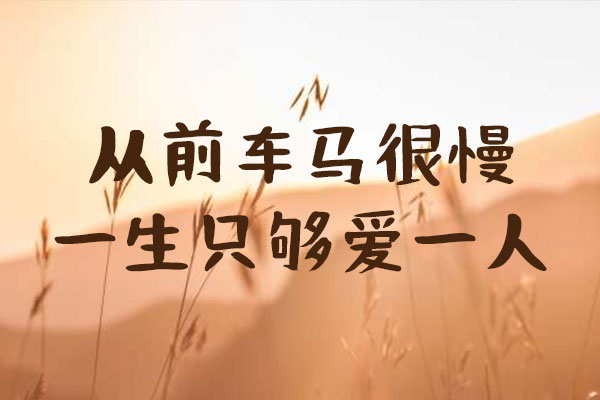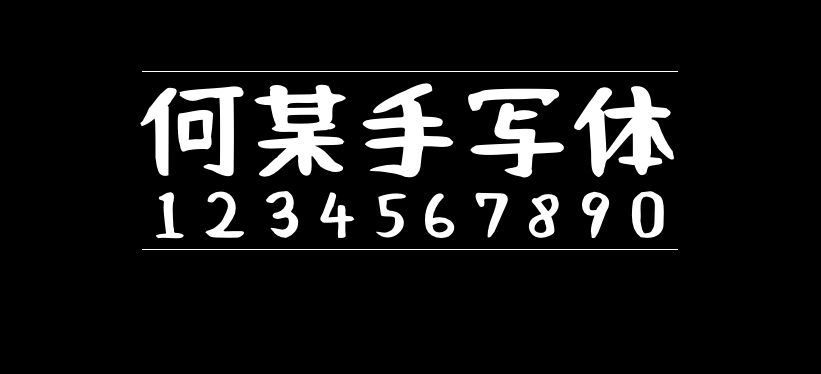
何某手写体
何某手写体(NaniFont、何某手寫)是Max基于日本的おつとめフォント字体(源字体遵循SIL开源字体协议)增补修改而成的一款自由手写体。与原作者的主要差异是调整部件写法、新增中文字、增加一些符号,值得一提的是增加4个字重,现一共拥有5个字重。经过Max的增补,何某手写体对简体的字体支持也挺不错的。
对现代人来说,毛笔字体不是可读性好的字体。但是手写文字和勘亭流等优秀的文字经常被用于促销用的传单和海报等。因此,何某手写体是根据毛笔文字的使用实际情况,重视“可视性高”为目标而制作的字体,大家不妨一试!